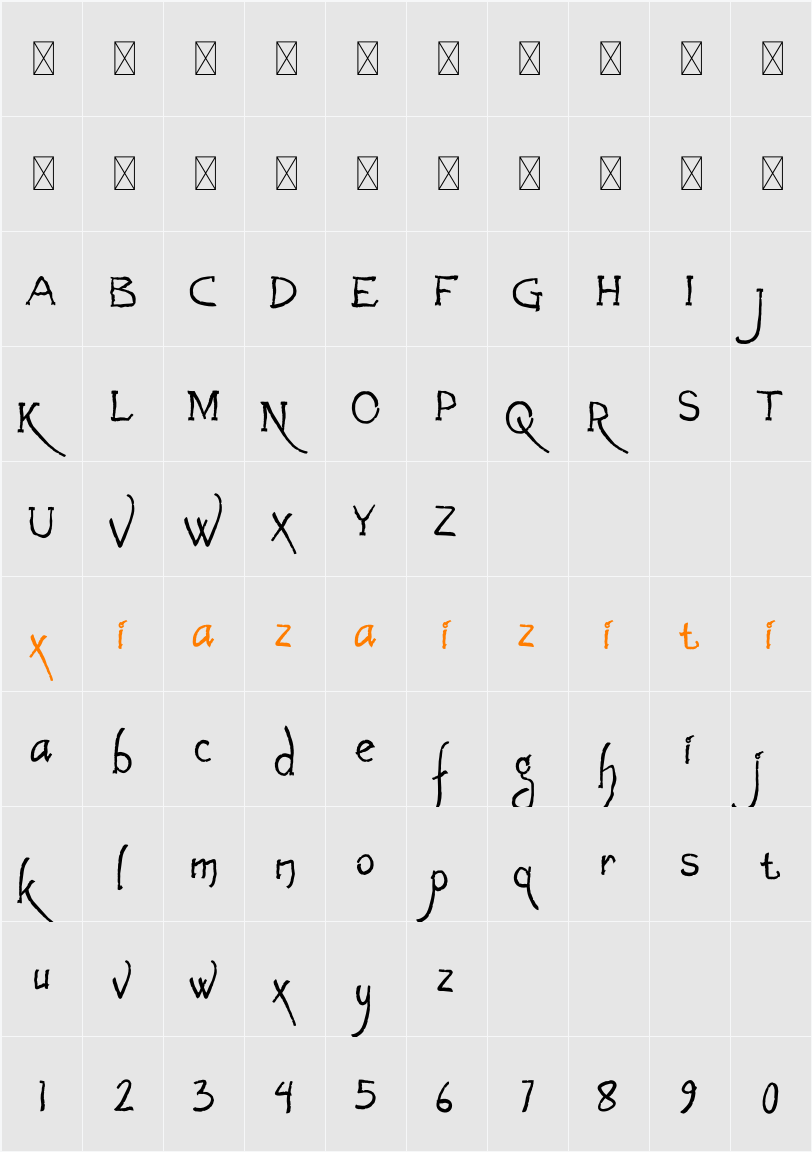
Wonder Raiders - Free Trial
Wonder Raiders - Free Trial,这款字体结构工整、笔画清晰,兼顾美观与易读性,适用于标题、正文、海报、包装、LOGO 等多种场景。字形优雅稳定,风格百搭耐看,适配日常排版与创意设计,让文字呈现更舒适、更具质感。Wonder Raiders - Free Trial一笔一画,皆是细节,以均衡的比例、流畅的线条打造舒适视觉体验,字形端正大气,风格简约现代。无论是商业设计、品牌宣传还是日常排版,都能轻松驾驭,让文字更有格调与力量。Wonder Raiders - Free Trial字体下载。